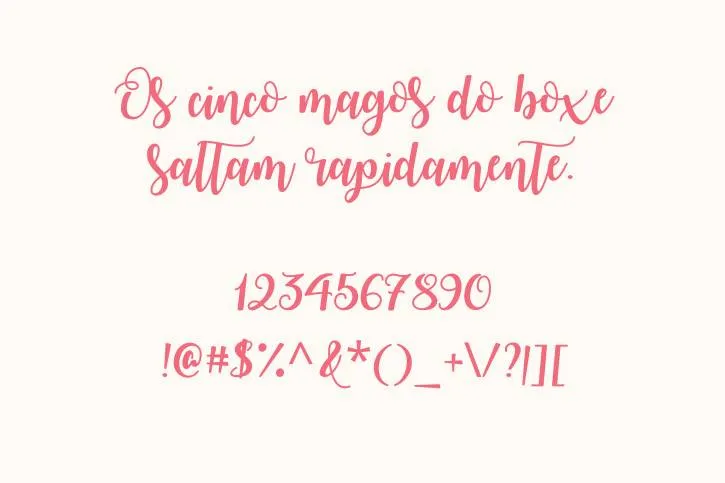
A fonte Watermelon Script é uma escolha diferenciada e cativante para projetos que exigem um toque de elegância e charme. Pertence à categoria de script e foi desenhado por Misti’s Fonts. Com seus traços suaves e fluidos, esta fonte transmite uma sensação de leveza e delicadeza. A sua estética caligráfica, inspirada na caligrafia, acrescenta um elemento de personalidade.
Uma das principais características é a variedade de opções de estilo. É ótimo para combinar com fontes semelhantes, como a Fonte Gabelisa, que é uma fonte famosa. Com diferentes alternativas de letras e caracteres alternativos, os designers podem personalizar facilmente. Isso permite maior flexibilidade criativa.
Além de sua estética atrativa, também oferece excelente legibilidade, garantindo que o texto seja facilmente compreendido pelos leitores. Seus caracteres bem desenhados e espaçamento cuidadosamente ajustado contribuem para uma experiência de leitura confortável. Outro aspecto atraente é sua versatilidade.
Características da Fonte Watermelon Script
É reconhecido pelas suas características distintivas que o tornam uma escolha popular entre designers e criativos. Suas principais características incluem:
Estilo Caligráfico: Apresenta um estilo caligráfico elegante, inspirado na caligrafia. A fonte Kasuki Hand pode ser usada para emparelhar para dar uma aparência massiva aos seus designs.
Versatilidade: É altamente versátil e pode ser usado em diversos contextos e mídias, tanto impressas quanto digitais.
Legibilidade aprimorada: Apesar de seu estilo ornamentado, a fonte mantém excelente legibilidade, garantindo que o texto seja facilmente compreendido pelos leitores.
Estética Charmosa: Com sua estética charmosa e sofisticada, agrega um toque de beleza e estilo aos designs.
Usando a Fonte per Watermelon Script em Designs
- Convites de casamento e artigos de papelaria para um toque elegante.
- Design de logotipo para adicionar um elemento pessoal e elegante.
- Embalagem de produto artesanal para um visual artesanal único.
- Gráficos de mídia social para transmitir uma vibração calorosa e amigável.
- Combine-a com a Cult para criar cabeçalhos e títulos de blogs para destacar o conteúdo.
- Cartões para uma mensagem personalizada e sincera.
- Cartazes artísticos e flyers para uma comunicação visual apelativa.
- Etiquetas de projetos artesanais e DIY para uma sensação caseira encantadora.
Imagem de Design da Fonte Watermelon Script
Qual é a fonte da fonte Watermelon Script?
Pertence à categoria de script e foi desenhado por Misti’s Fonts.
O que a fonte Watermelon Script apresenta?
Esta fonte escrita apresenta linhas suaves e fluidas, que transmitem uma sensação de leveza e delicadeza.